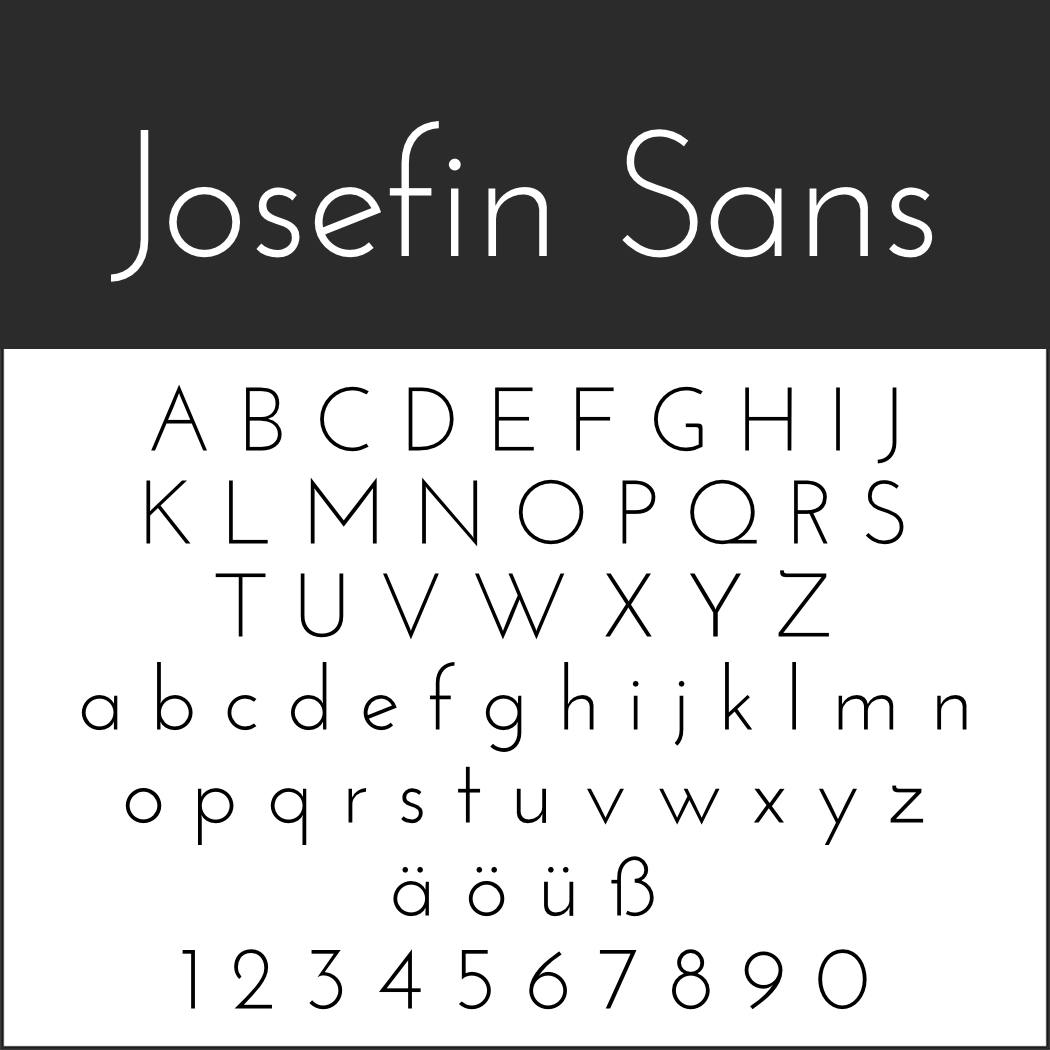
Was macht eine nordische Schriftart aus? Lässt sie die Wikinger-Ära vor unseren Augen wieder erstehen oder steht sie für zeitgemäßes skandinavisches Design? Sowohl als auch, finden wir. Deshalb haben wir uns in beiden „Lagern“ für Sie umgeschaut und einige kostenlose Download-Fonts zur kommerziellen Nutzung zusammengestellt.
Nordische Schriftart gratis herunterladen
Damit Sie sich besser zurechtfinden, beginnen wir mit den „alten“ nordischen Schriftarten und präsentieren Ihnen im Anschluss moderne Varianten.
„Traditionelle“ nordische Schriftart
Wikinger, Normannen, Eroberungszüge und große Entdeckungen: Die Epoche der Seefahrer aus dem Norden ist reich an Erzählungen und Mythen. Ein Hauch davon schwingt in jedem dieser Fonts mit, die teils an alte Schriften angelehnt sind.
Nordische Schriftart: NorseNorse
Der englische Begriff „norse“ bedeutet „nordisch“ – und folgerichtig orientierte sich der französische Designer an Runen, um seine Buchstaben zu schaffen.
Nordische Schriftart: VikingViking
Die Vorbilder für Viking führen uns in das frühe Mittelalter zurück. Kein Zufall, dass sich der Name auf die seefahrenden Krieger aus dem Norden bezieht.
Schriftart: Twinkling
Mit „glitzernd“ oder „funkelnd“ lässt sich „twinkling“ übersetzen – und der Name ist Programm. Insofern passt dieser Font vor allem für besonders glänzende Angebote.
Nordische Schriftart: Jorvik Informal
Als Vorlage dienten dem deutschen Designer alte Schriften, aber auch ein neuerer Entwurf: eine Schrift aus dem Jahr 1966 des Typografen Georg Salden.
Gebrochene Schrift: FDI Wiking
Die gebrochene Schrift im Wikinger-Stil geht auf eine Schrift von Heinz König für die Schriftgießerei J. D. Trennert & Sohn in Hamburg aus dem Jahr 1925 zurück.
Moderne nordische Schriftart
Scandi-Chic und nordeuropäische Lässigkeit strahlen die folgenden Fonts aus. Da der skandinavische Bezug nicht offensichtlich ist, eignen sich diese Schriftarten für nahezu alle Themen.
Moderne nordische Schriftart: PTF NORDIC Rnd Lt
Der japanische Designer hinter diesem Font hat eine komplette Schriftfamilie unter dem Namen Nordic entwickelt.
Nordische Schriftart: Jann Script
Die Schrift hat zunächst keine besonders nordeuropäische Anmutung. Der in Kopenhagen lebende finnische Designer hat allerdings nahezu alle skandinavischen Sonderzeichen integriert, so dass wir hier durchaus das Prädikat „nordische Schriftart“ vergeben.
Skandi Schriftart: SkranjiSkranji
Nach Ansicht des Designers verbindet Skranji den „Donner der nordischen Götter“ mit der „Nützlichkeit eines Schweizer Taschenmessers“.
Nordische Schriftart: Josefin Sans
Mit Josefin Sans wollte der Designer schwedisches Design mit historischen Schriften kombinieren. Pate standen Kabel (1927) von Rudolf Koch, Memphis (1930) von Rudolf Wolf  und die berühmte Futura (1927) von Paul Renner.
Skandi Schrift: AllerAller
Den vielseitigen Font mit sieben Schriftschnitten entwickelte ein Londoner Studio für die Danmarks Medie- og Journalisthøjskole (Dänische Medien- und Journalistenschule) in Kopenhagen und Aarhus.
Nordische Schriftart: Krona One
Die deutsche Designerin ließ sich für Krona One von schwedischen Handlettering-Postern aus dem frühen 20. Jahrhundert inspirieren.